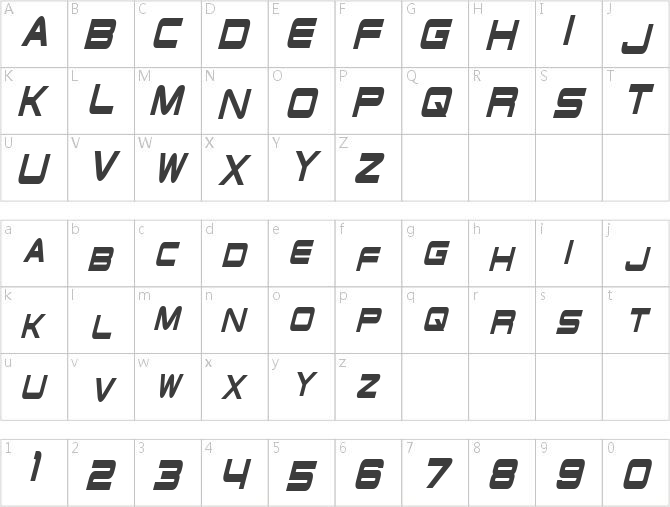
Schwarzenegger Condensed Italic
Schwarzenegger Condensed Italic字體字庫是一款讓人賞心悅目、百看不厭的英文字體,適合各類廣告和產(chǎn)品包裝設計應用,字體大小0.09MB,格式為ttf字體,上傳用戶是順新廣告?,作者/版權方為未知